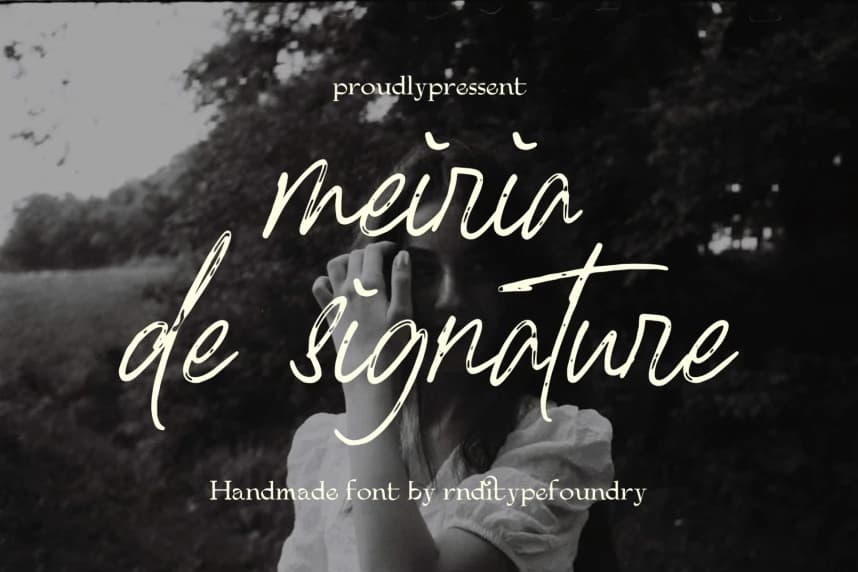
Meiria De İmzalı Yazı Tipi
Meiria De Signature Font, modern kaligrafinin doğal güzelliğini ve kişisel imza stilini yakalayan zarif bir el yazısı fontudur. Yumuşak akışlı hatlar, zarif eğriler ve rafine harf bağlantılarıyla öne çıkar.
Meiria De Signature Font, zarif bir el yazısı fontudur ve modern kaligrafi ile kişisel imza stilinin doğal güzelliğini yakalar. Akıcı hatlar, zarif eğriler ve rafine harf bağlantıları ile öne çıkar.